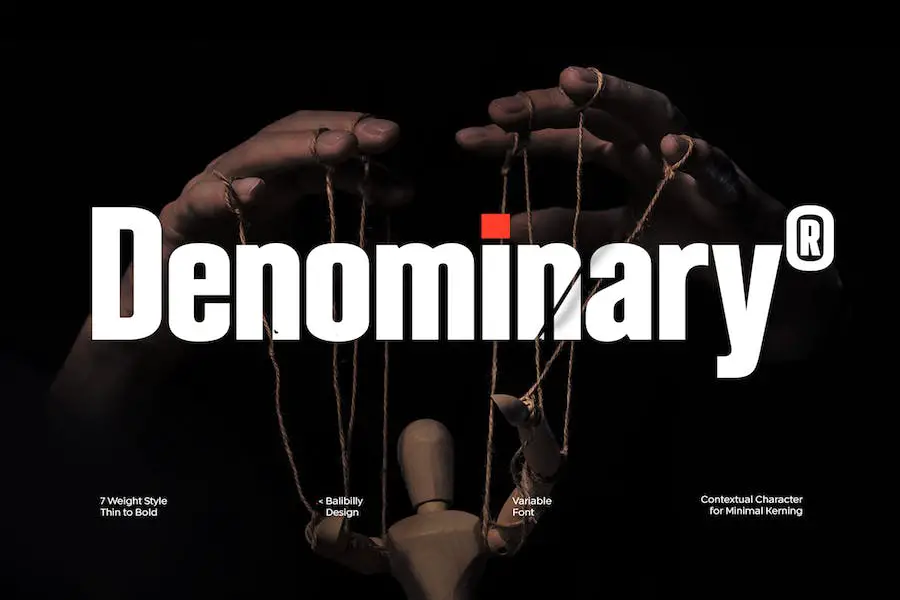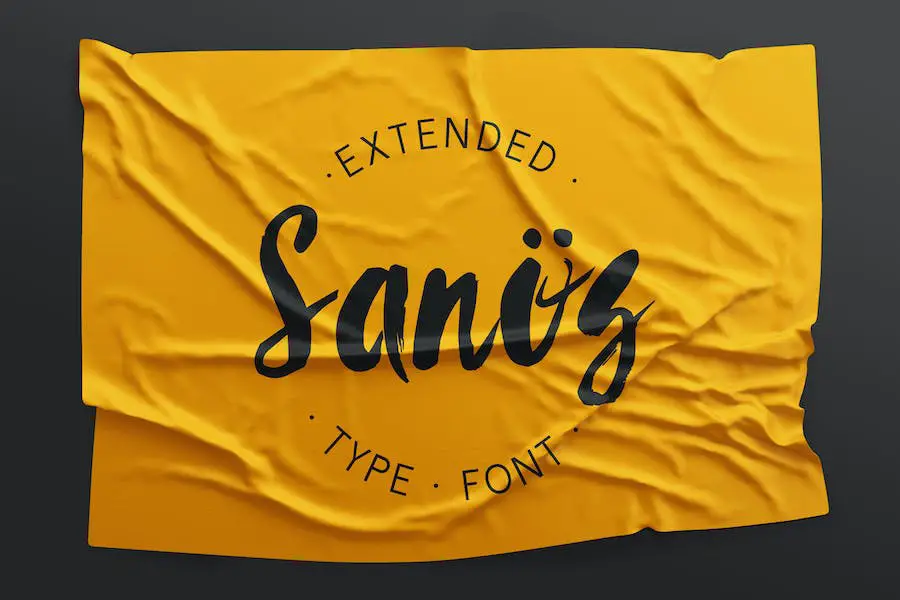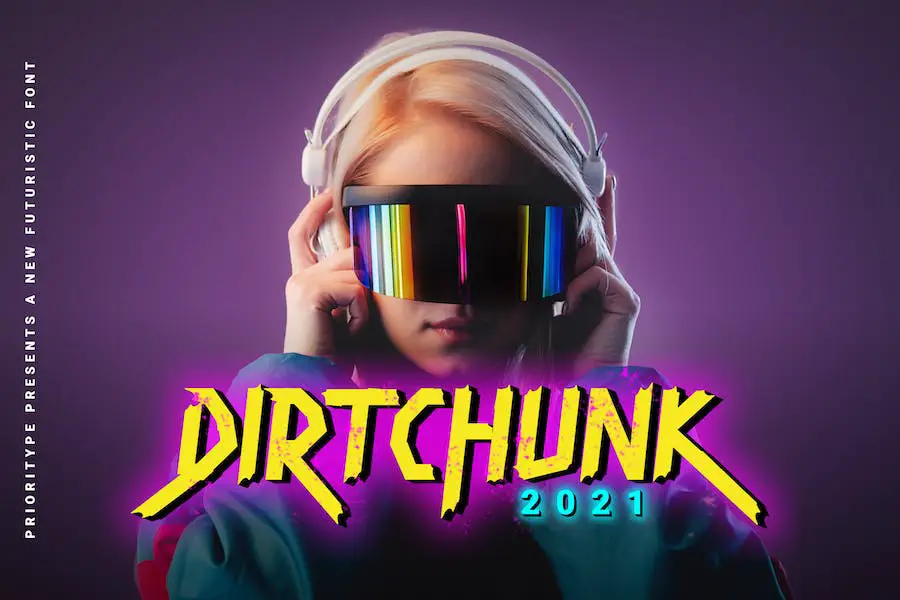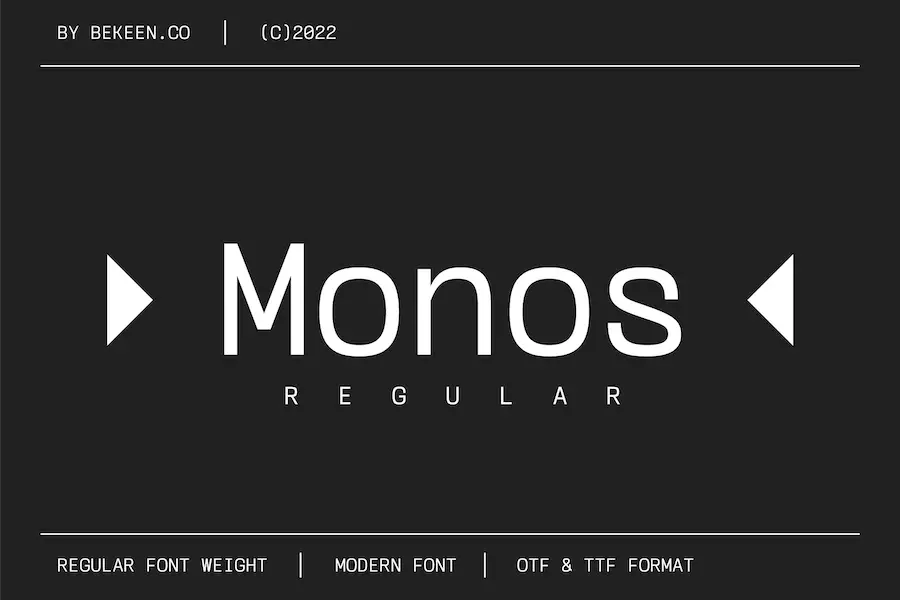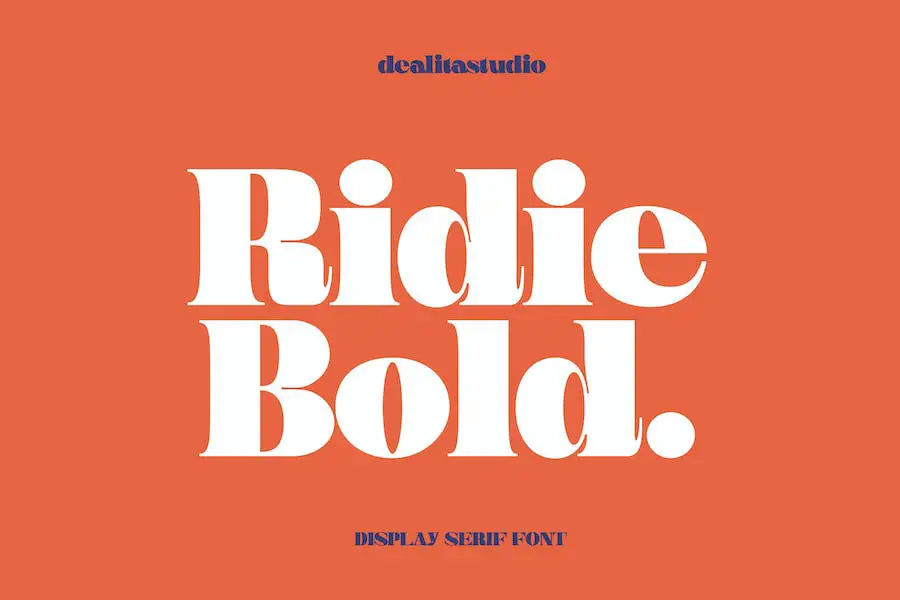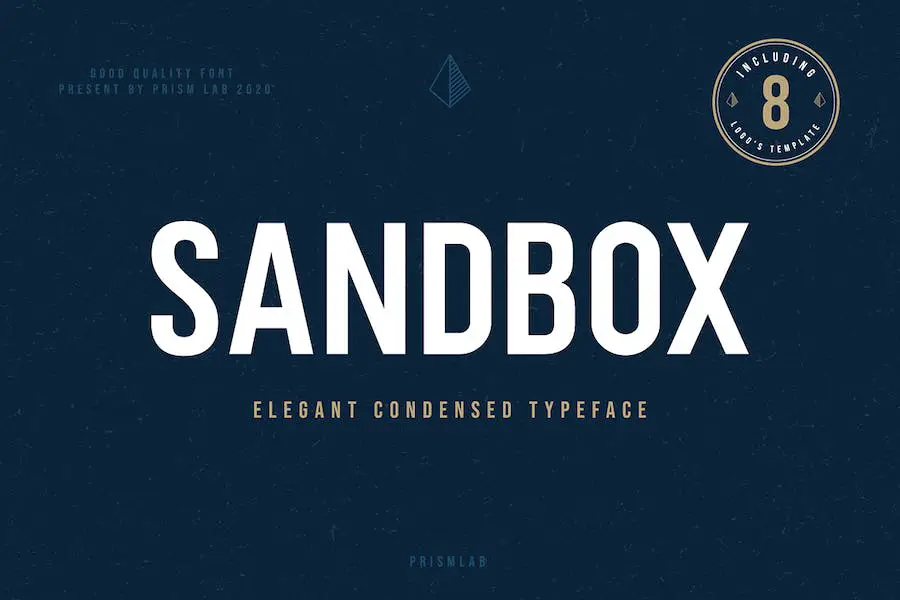
Las 21 mejores fuentes para aplicaciones 2023 (gratuitas y premium)
Publicado: 2023-08-24¿Es usted un diseñador gráfico que busca la fuente perfecta para mejorar los diseños de su aplicación? ¡No busque más! En esta publicación de blog, hemos seleccionado una lista de las 21 mejores fuentes para aplicaciones que mejorarán el atractivo visual y el diseño general de sus proyectos.
Entendemos la importancia de encontrar la fuente adecuada para que su aplicación se destaque, ¡así que profundicemos y exploremos las opciones!
Cuando se trata de diseño de aplicaciones, elegir la fuente adecuada puede marcar la diferencia. ¿Sabías que los estudios han demostrado que el uso de las fuentes adecuadas puede mejorar la legibilidad y la participación del usuario? ¡Es cierto!
Y es por eso que hemos elaborado esta lista completa de las mejores fuentes para aplicaciones. Ya sea que esté diseñando una aplicación de juegos, una aplicación meteorológica o una aplicación de productividad, lo cubrimos con opciones que no solo son visualmente atractivas sino que también están optimizadas para su legibilidad en varios tamaños de pantalla y dispositivos.
Entonces, ¡echemos un vistazo más de cerca a nuestras principales recomendaciones de fuentes!
En este artículo, le presentaremos una selección minuciosa de fuentes que son perfectas para diseños de aplicaciones. Cada fuente ha sido elegida cuidadosamente en función de su versatilidad, legibilidad y atractivo estético.
¡Prepárate para llevar los diseños de tus aplicaciones al siguiente nivel con estas 21 mejores fuentes para aplicaciones!
Las mejores fuentes premium para aplicaciones
¿Buscas darle al diseño de tu aplicación un toque pulido y profesional? ¡No busque más! En esta sección, mostraremos las mejores fuentes premium que llevarán su aplicación al siguiente nivel.
Con estas fuentes, puedes agregar un toque de elegancia, personalidad o alegría a la interfaz de tu aplicación. Entonces, sin más preámbulos, ¡profundicemos y exploremos las fuentes que seguramente mejorarán el diseño de su aplicación!
oso de lujo
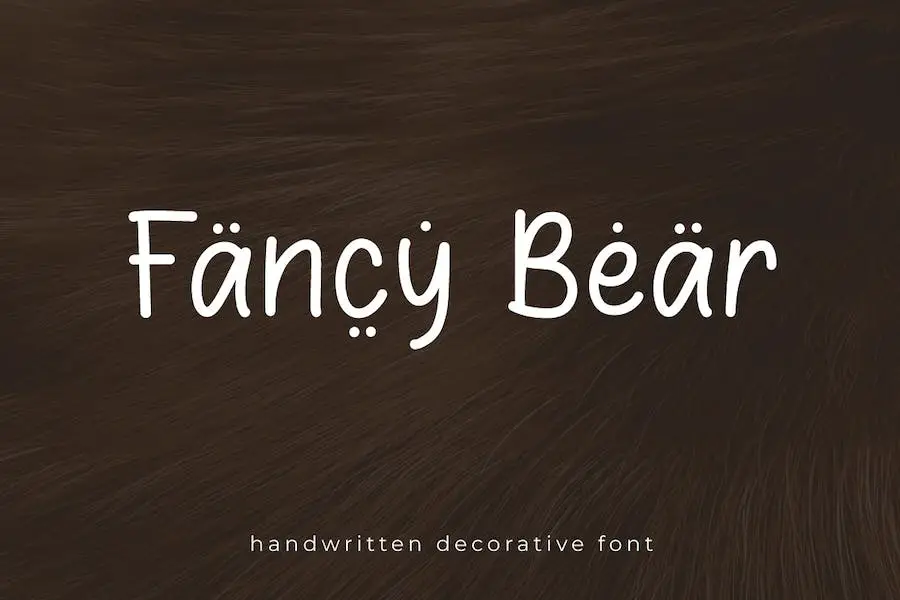
Fancy Bear es una fuente moderna que puede añadir un toque de elegancia y creatividad a cualquier proyecto de diseño gráfico. Con su estilo decorativo escrito a mano, es perfecto para diversos fines, incluidos libros para niños, tarjetas de cumpleaños, fuentes de aplicaciones, logotipos web, títulos de libros y logotipos de revistas.
Esta fuente aporta un toque único y personal a tus diseños, haciéndolos destacar entre la multitud. Su aspecto lúdico y caprichoso lo hace especialmente adecuado para proyectos dirigidos a un público más joven o aquellos que requieren un toque de diversión y creatividad.
Ya sea que esté diseñando la portada de un libro para niños o creando un logotipo web atractivo para una aplicación, Fancy Bear puede ayudarlo a lograr la apariencia deseada. Su versatilidad le permite adaptarse a varios estilos y temas de diseño, lo que lo convierte en una opción flexible para cualquier diseñador gráfico.
biogema
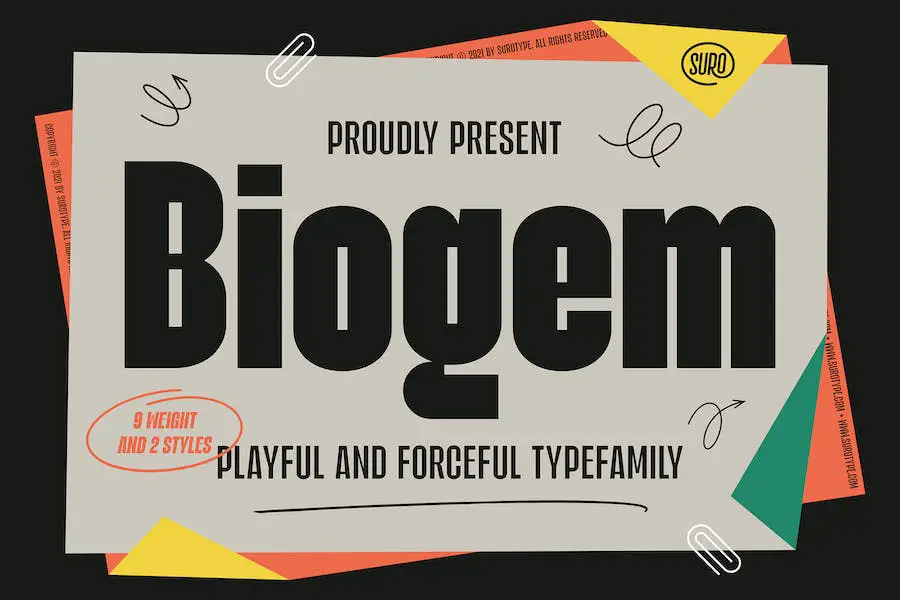
Biogem es un tipo de letra divertido y contundente que ofrece 18 fuentes con estilos simple y cursiva. Con 9 pesos que van desde fino hasta negro, ofrece una amplia gama de opciones para los diseñadores gráficos que buscan mejorar sus proyectos.
Esta fuente versátil es perfecta para añadir un toque de personalidad e impacto a cualquier diseño. Ya sea que necesite un título atrevido y llamativo o un cuerpo de texto limpio y profesional, Biogem lo tiene cubierto.
Su variedad de pesos y estilos permiten una creatividad y personalización infinitas. Dale a tus diseños un aspecto único y cautivador con la colección de fuentes de Biogem.
Ghumo
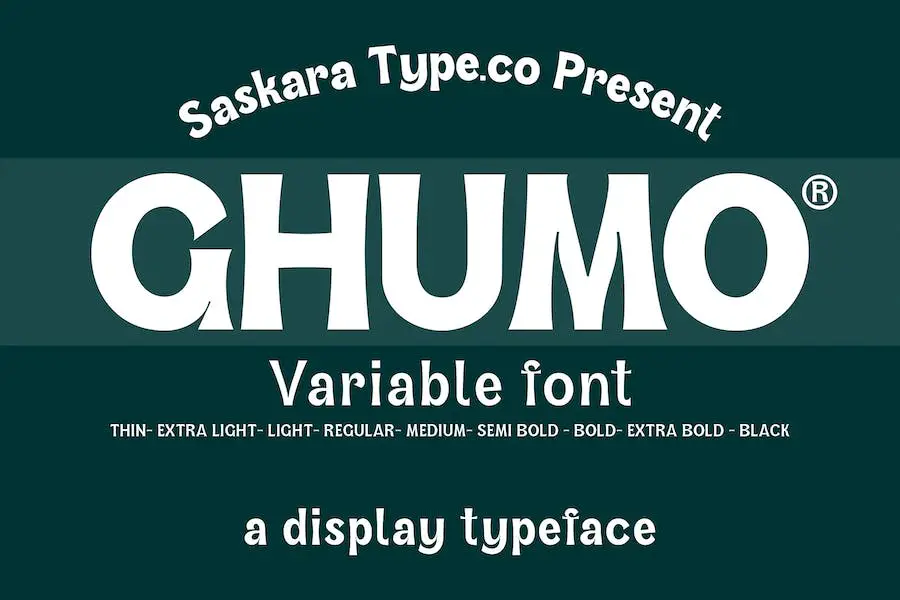
Ghumo es un tipo de letra fantástico que aporta diversión y potencia a tus proyectos. Con su colección de nueve fuentes, ofrece una gama de estilos modernos para mejorar sus diseños.
Ya sea que estés creando gráficos para aplicaciones, usando Canva o trabajando con Cricut, Ghumo es la elección perfecta para agregar un toque de personalidad y sofisticación a tu trabajo.
Su versatilidad y encanto único lo convierten en una herramienta indispensable para los diseñadores gráficos, elevando la estética general del diseño y captando la atención. Entonces, si estás buscando fuentes que lleven tus proyectos al siguiente nivel, definitivamente vale la pena considerar Ghumo.
Maduratna
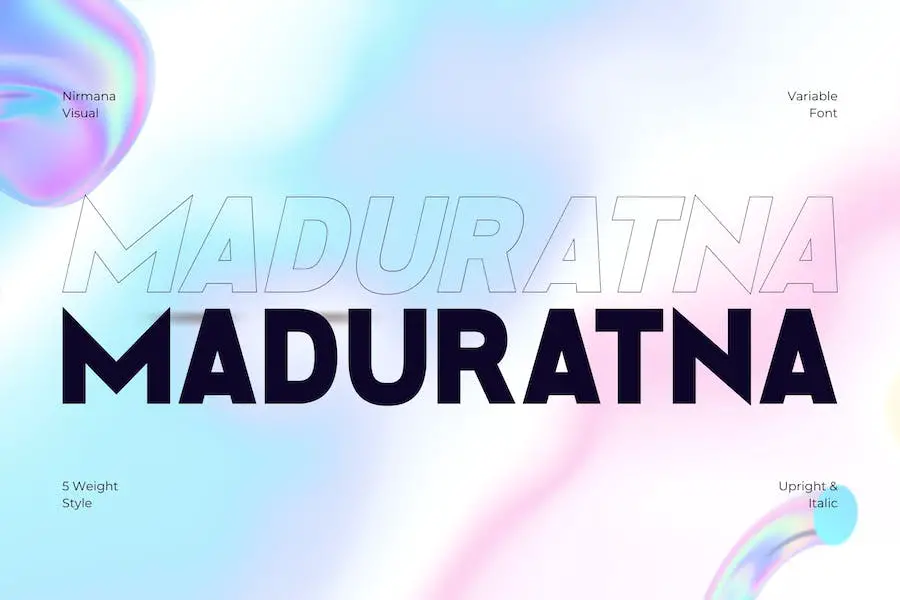
Maduratna es una familia de fuentes sans-serif única y divertida que viene en 5 pesos diferentes. Es perfecto para una amplia gama de proyectos de diseño, como logotipos y marcas, publicaciones en redes sociales, anuncios y diseños de productos.
La fuente ofrece una hermosa armonía tipográfica que puede mejorar el diseño general de sus proyectos. Ya sea que esté trabajando en un proyecto de marca profesional o en una publicación creativa en las redes sociales, Maduratna tiene la versatilidad para realzar sus diseños y hacerlos destacar.